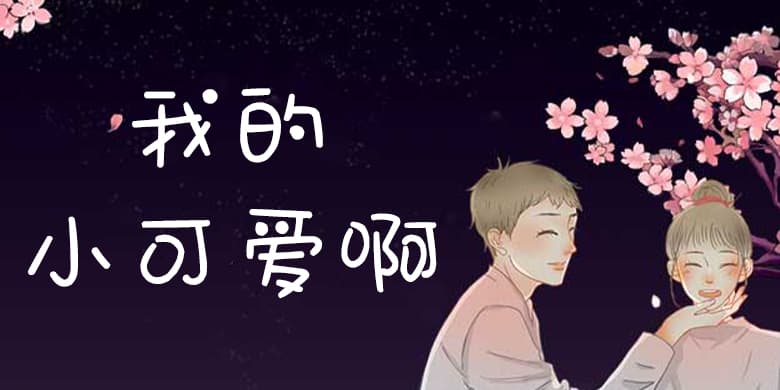
品牌:方正手迹设计师:俞亦婷发行时间:2019字库编码:大陆简体(GB2312-80)分类:创意书写字体属性:精品字
我的小可爱啊是一款风格可爱的手写字体。笔画中用小圆点代替部分笔画,笔画转折圆润,显得生动有趣。适用于少儿类书刊,及现代诗歌、短文的排版以及文化、商业类品牌的广告语设计。
品牌:方正手迹设计师:俞亦婷发行时间:2019字库编码:大陆简体(GB2312-80)分类:创意书写字体属性:精品字
我的小可爱啊是一款风格可爱的手写字体。笔画中用小圆点代替部分笔画,笔画转折圆润,显得生动有趣。适用于少儿类书刊,及现代诗歌、短文的排版以及文化、商业类品牌的广告语设计。